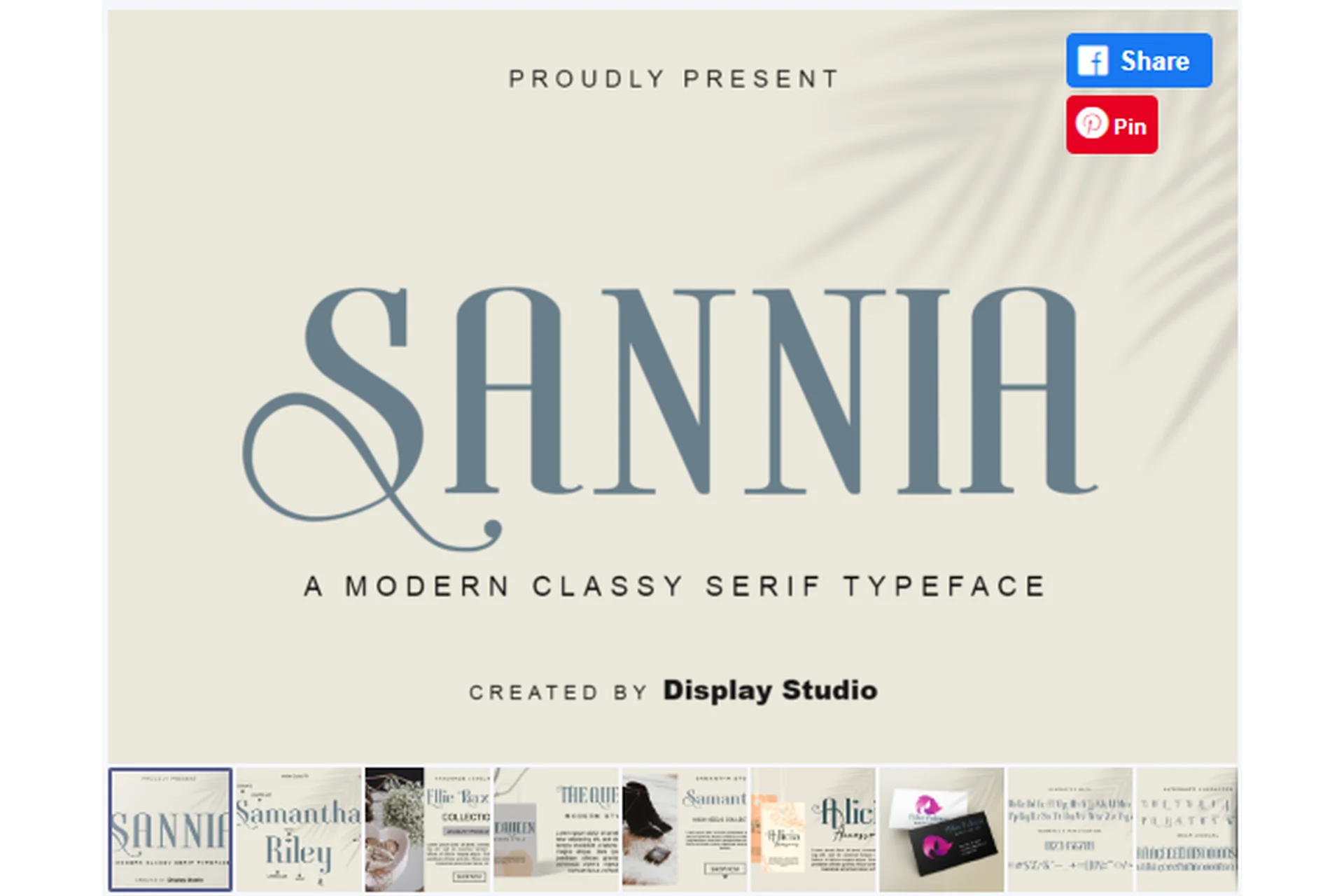
​ Sannia Современный классический шрифт с засечками. Он идеально подходит для логотипов брендов, приглашений, поздравительных открыток и любых творческих проектов. Благодаря многоязычным возможностям и стилевым вариациям, этот шрифт еще больше подчеркнет эстетический аспект вашей работы. Этот шрифт закодирован в PUA, что означает, что вы можете легко получить доступ ко всем глифам и штрихам!